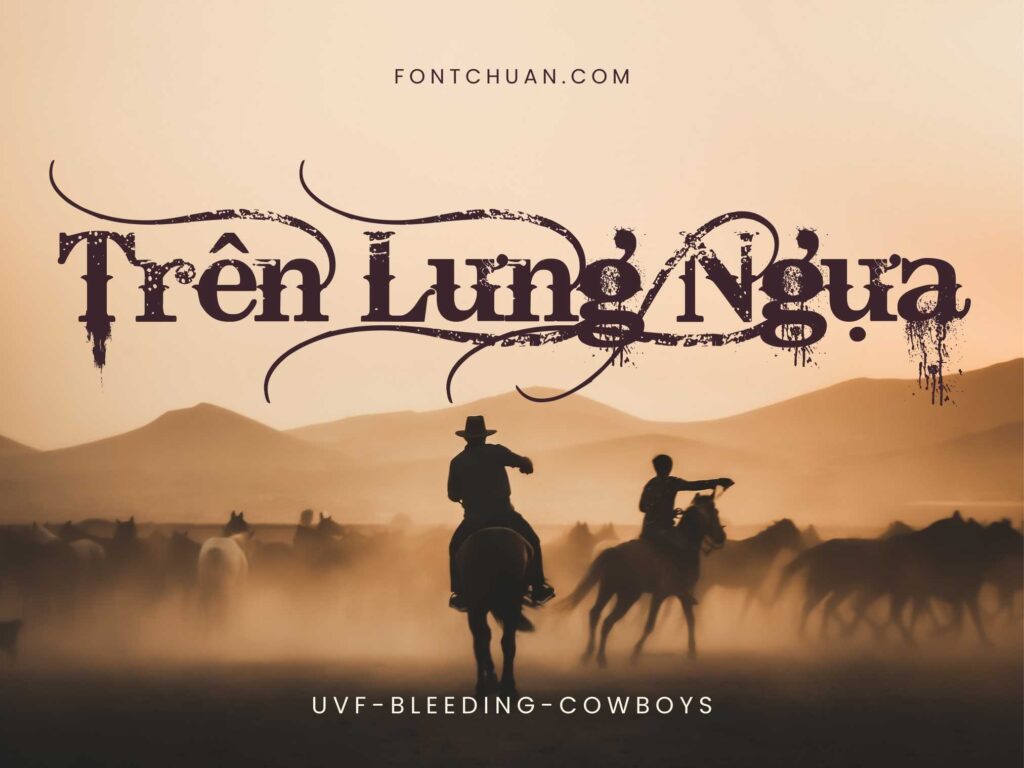
UVF Bleeding Cowboys là một phông chữ thuộc thể loại Western, được thiết kế bởi Segments Design (còn được gọi là Last Soundtrack). Phông chữ này nổi bật với phong cách grunge độc đáo, mang lại cảm giác hoang dã và phong trần, phù hợp cho các thiết kế liên quan đến chủ đề miền Tây nước Mỹ, nhạc rock, hoặc các dự án cần sự phá cách và nổi loạn. Phông chữ này đã được sưu tầm và đăng bởi thành viên của Font Chuẩn.